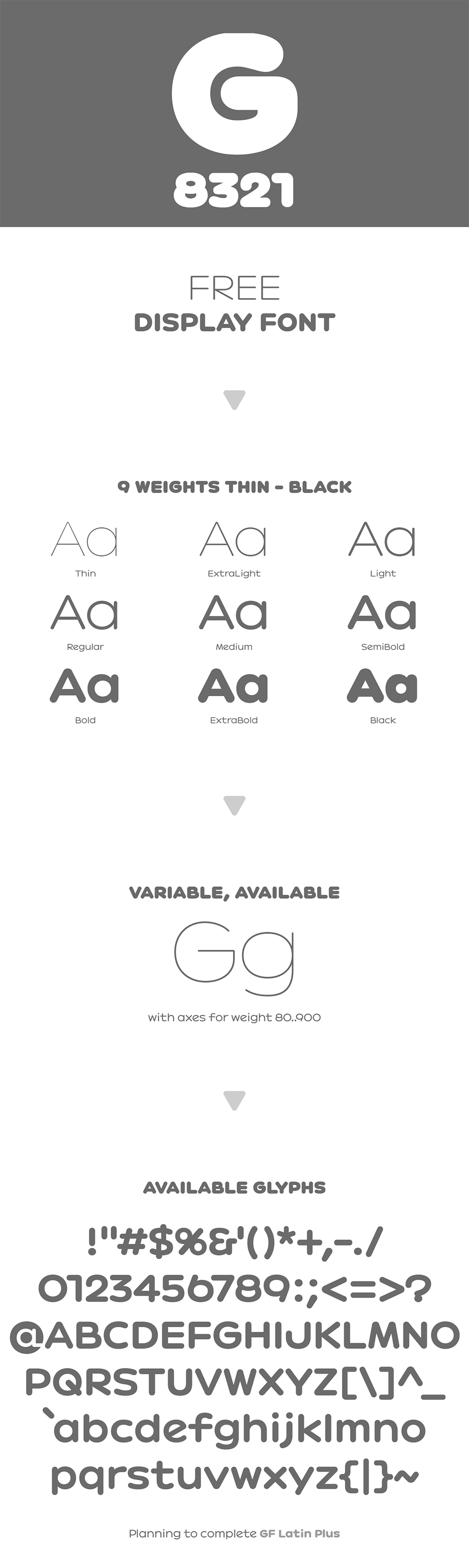
G8321 2026年4月1日 下午8:04 • 英文字体 • 阅读 255 目录 字体预览字体风格字体下载 G8321 是一款支持免费商用的开源字体,一共包含 9 种字重,同时还提供了可变字体版本。 字体预览 G8321 选择预设预览文本 选择预设文字 Hello, World 1234567890 !@#$%^&*()_+,. A- A+ 自定义预览文本 选择字体字重 Thin ExtraLight Light Regular Medium SemiBold Bold ExtraBold Black 字体风格 G8321 主打现代感与实用功能,字形轮廓清晰利落,笔画扎实稳重。搭配可变字体特性,只用一个字体文件,就能实现从纤细精致到厚重有力的风格切换,适配不同排版场景的需求。 字体下载 G8321 下载次数 15 字体类型 无衬线 授权协议 OFL 授权类型 免费商用 刷新 OFL无衬线英文标题字体 赞 (0) 0 0 生成海报 相关推荐 英文字体 Iosevka 是一款面向现代编程场景设计、高度可定制的等宽字体,专为代码编辑优化而生。它的核心设计思路,是在有限的横向宽度里显示更多内容,同时保证长时间写代码也能清晰易读。字形整体偏窄高,相同字号下比普通等宽字体能显示更多列代码,在编辑器里效率更高。 2026年4月2日 2120 英文字体 E1234 E1234 是一款设计灵感源于电子闹钟或早期数字显示屏的免费开源英文字体,以其独特的数码风格和广泛的语言支持为特点。其设计模仿了七段数码管或电子时钟的显示效果,字符由简洁的直线段构成,形成鲜明的几何图形感。 2026年1月13日 2820 英文字体 Cabin Cabin 是一款将人文主义温情与现代几何感结合在一起的开源无衬线字体,由 Pablo Impallari 设计。它借鉴了 20 世纪初爱德华・约翰斯顿与埃里克・吉尔的经典人文主义字体风格,再结合当代使用需求重新优化而成。字体共有四种字重,每一款都配有专门设计的真斜体,而非简单拉伸变形,整体比例与光学效果都经过细致调整。 1天前 2440 英文字体 Help Me 是一款模拟在粗糙表面(如混凝土或木质)上划伤痕迹的免费英文字体,以其原始、粗粝的手工质感为特征。其设计核心在于完全模仿手工划刻的视觉效果,包含了英文大小写字母、数字及基本标点符号在内的 104 个字形。 2026年1月11日 2900 英文字体 Inter Inter 是一款打磨得十分精细的通用型字体,从 Thin(100)到 Black(900)一共提供了九个完整字重,并且对 100、400、900 这几个核心字重里的每个字符都单独做了优化,不管用多粗多细,显示效果都很稳定。它自带标准的意大利斜体,同时针对小字号阅读和大标题展示做了双重优化。字体里还集成了丰富的 OpenType 功能,比如会根据相邻字符自动调整的标点、带斜杠方便和字母 o 区分的数字 0,以及等宽数字等实用设计。 2026年4月1日 4010 发表回复 请登录后评论...登录后才能评论 提交